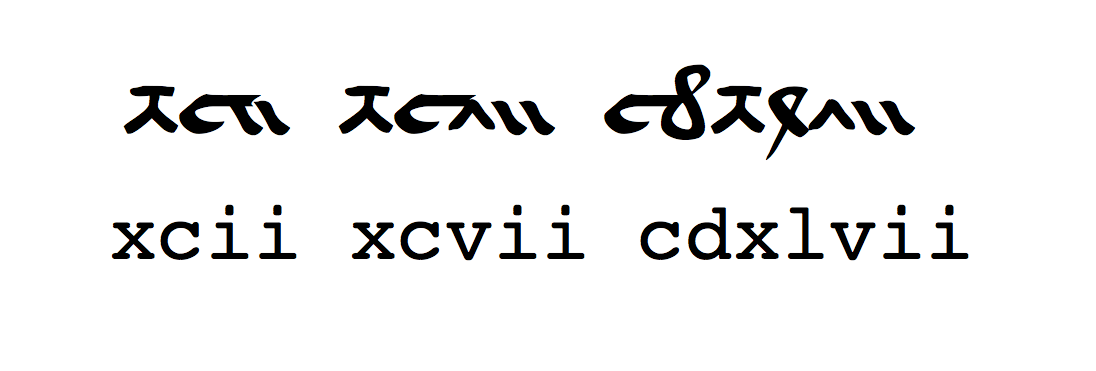
Welche Schriftart ist das?
ich bin auf der Suche nach der Schriftart (siehe Anhang).
Ich weiß nur, dass diese Schriftart VYLCH oder so ähnlich lautet und dass diese aus dem 15. Jahrhundert stammt.
Dann wäre das hier wohl der passende Link zum Font ...